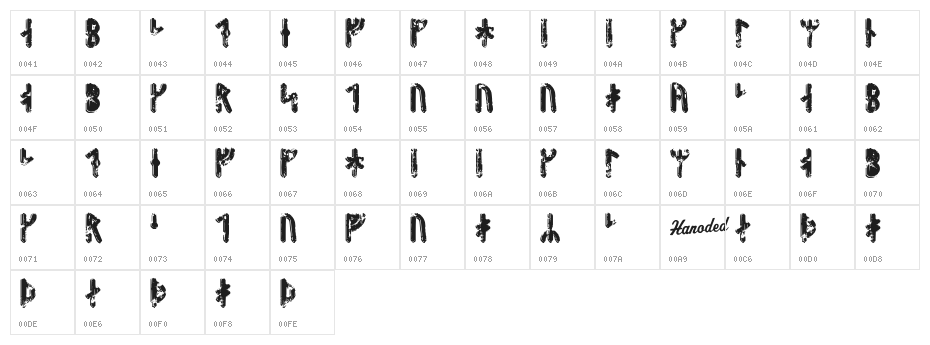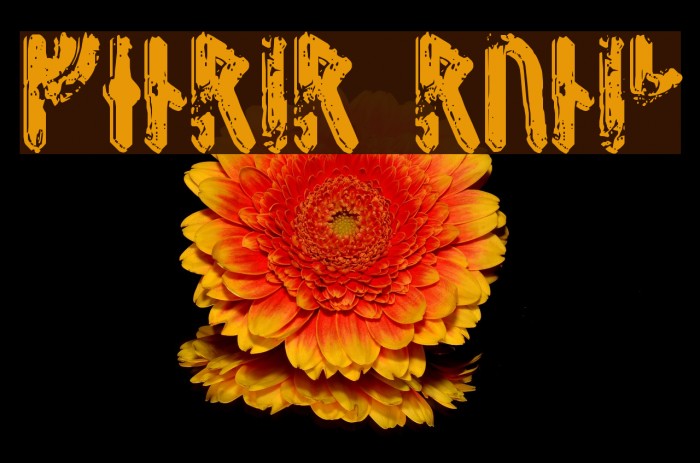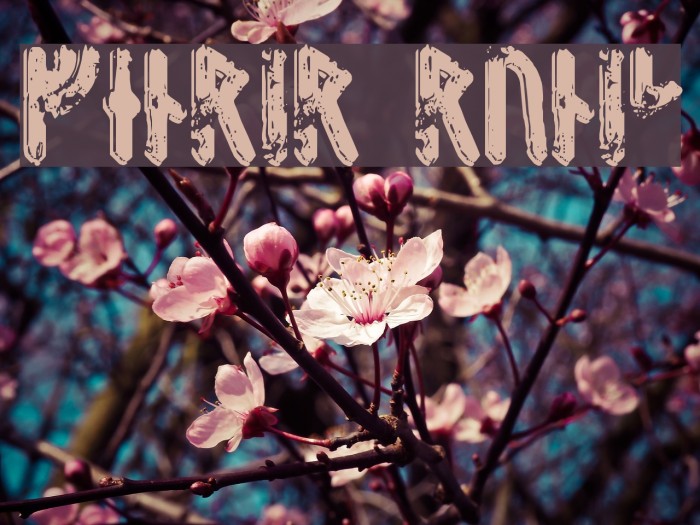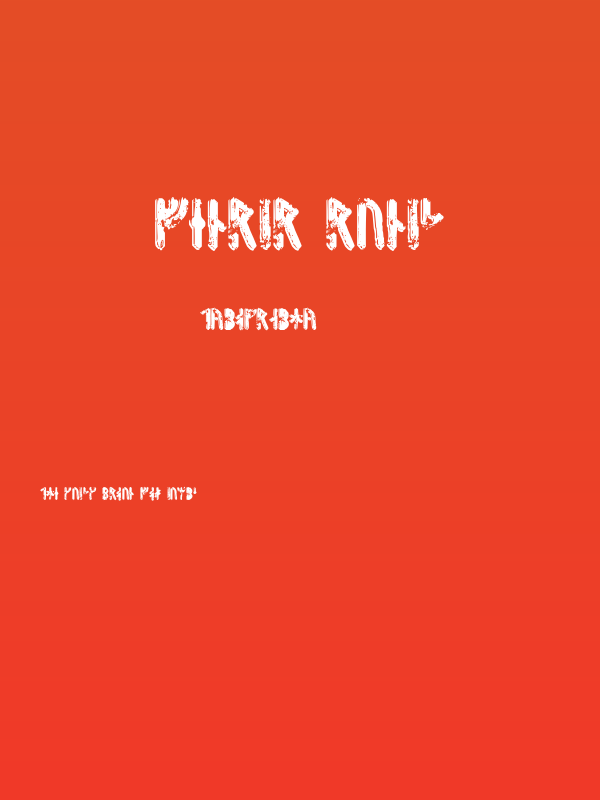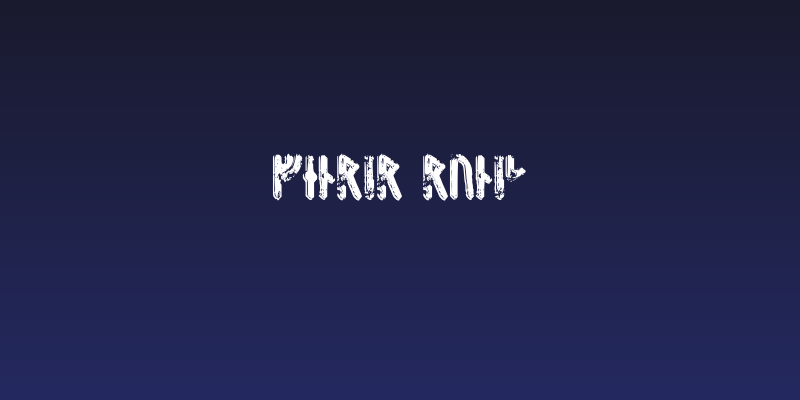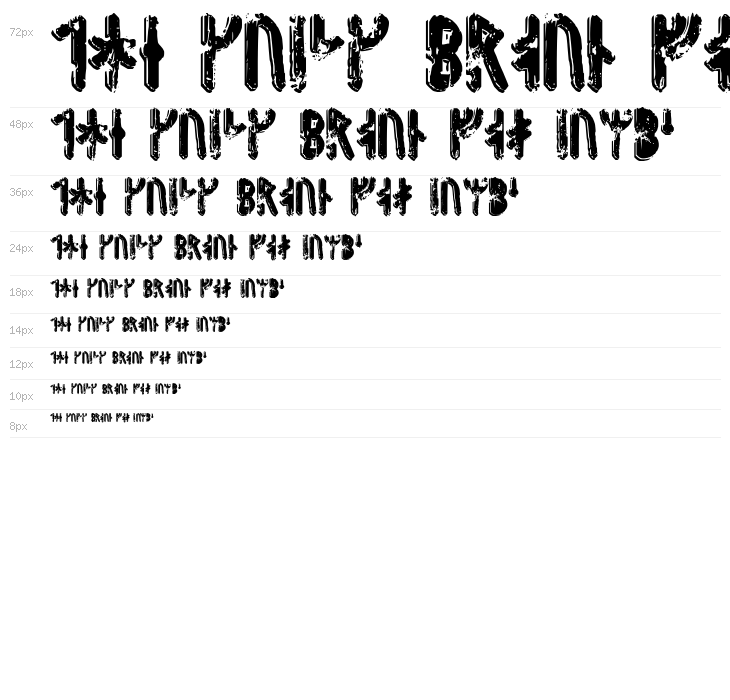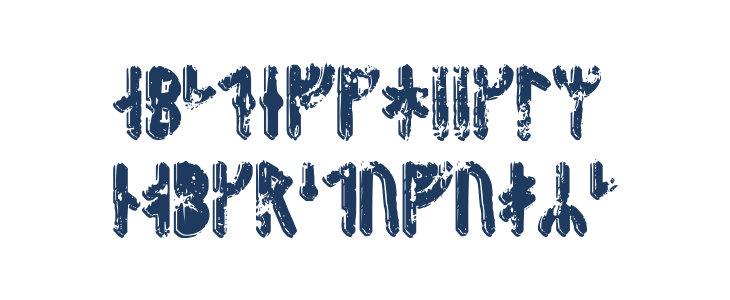
Fenrir Runic Font
| Caso d'uso | Logos, Headlines, Thematic Posters |
| Progetti proposti | Ideal for fantasy-themed designs, game titles, movie posters, and historical recreations. |